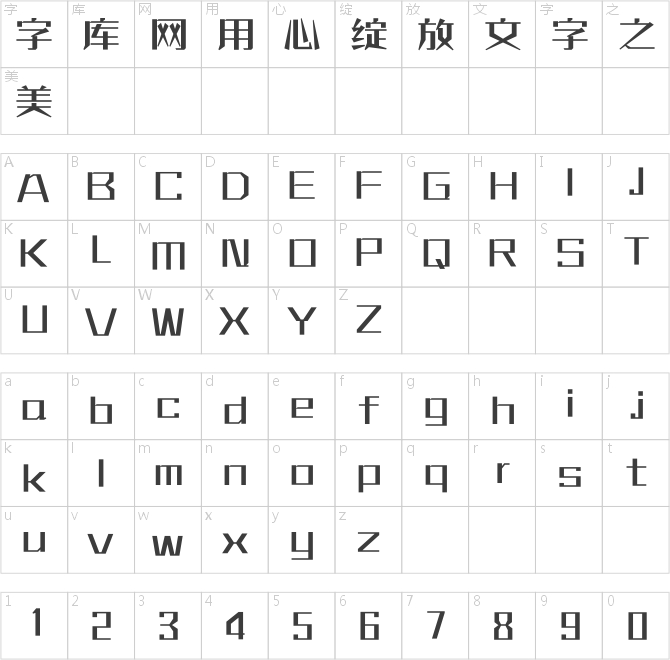
字体名称: 方正新恒刀刃体
方正新恒刀刃体
方正新恒刀刃体介绍
方正新恒刀刃体是在老式板报类字体的基础上进行改良规范的,该字体所有笔画全部以直线表现,撇、捺、点、勾收尾处均采用切角处理,似刀头、似利刃,故取名刀刃体,是一款既有力量感,又有活跃感,既有民国时期的风格,又具备新时代气息的字体。适用于海报招贴、视频媒体、产品包装、书籍报刊及周边领域。